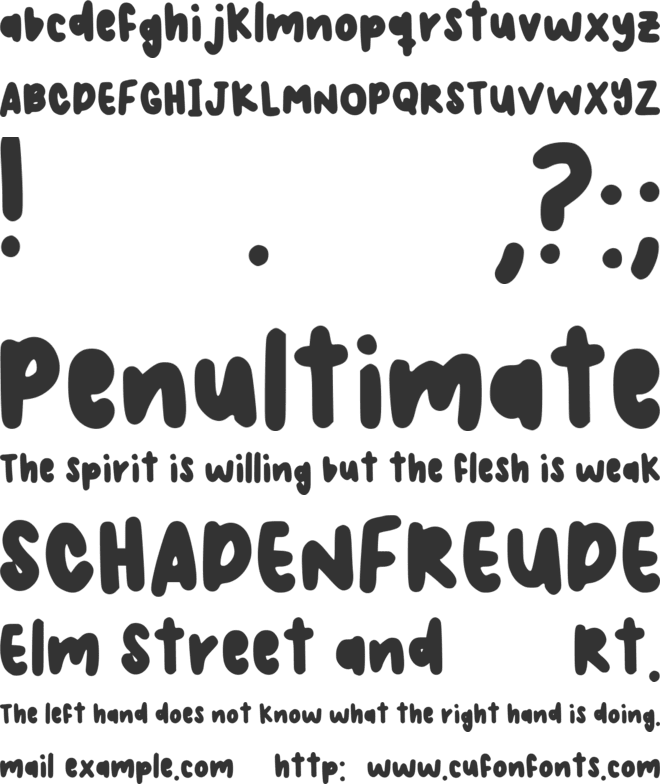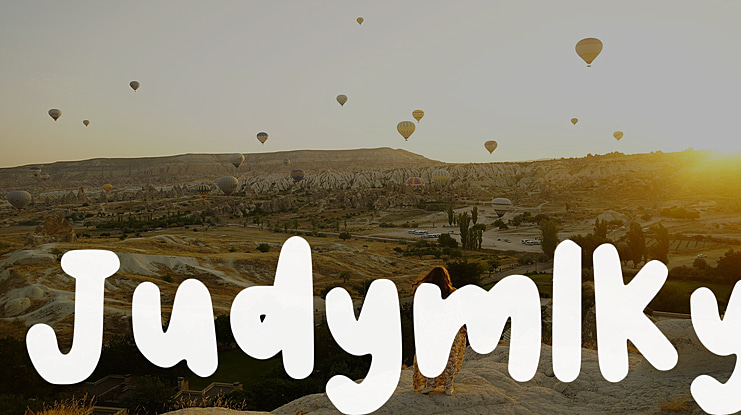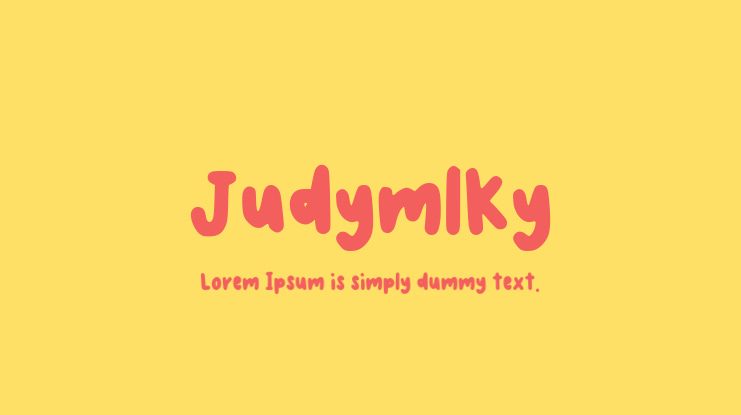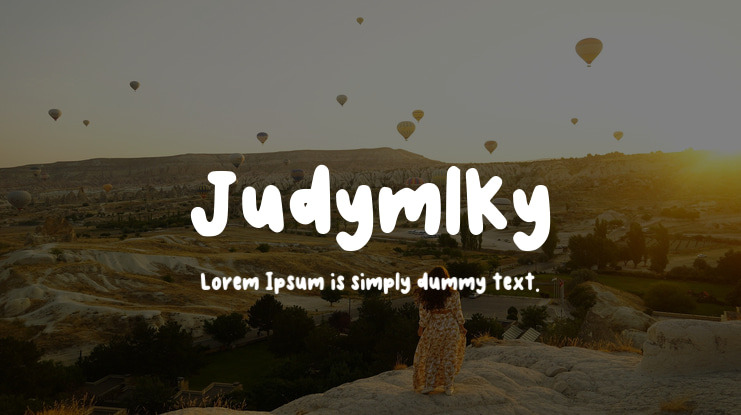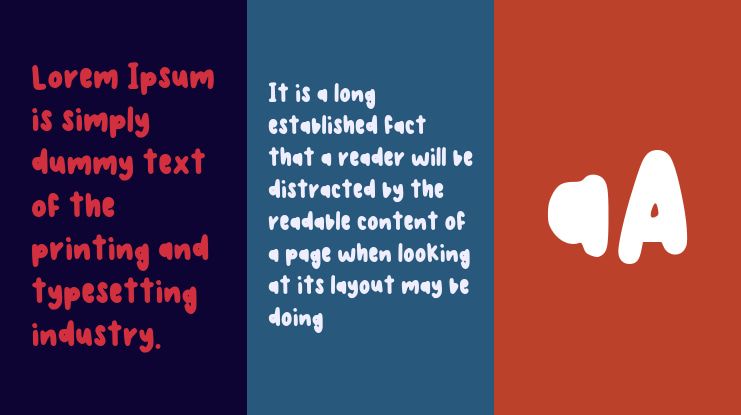
Judymlky Font
Espero les guste esta tipografía, ya que está basada en el tipo de letra que uso en mi día a día. Al ser la primera vez que hago una en vía digital, puede que contenga errores, así que una disculpa de antemano.